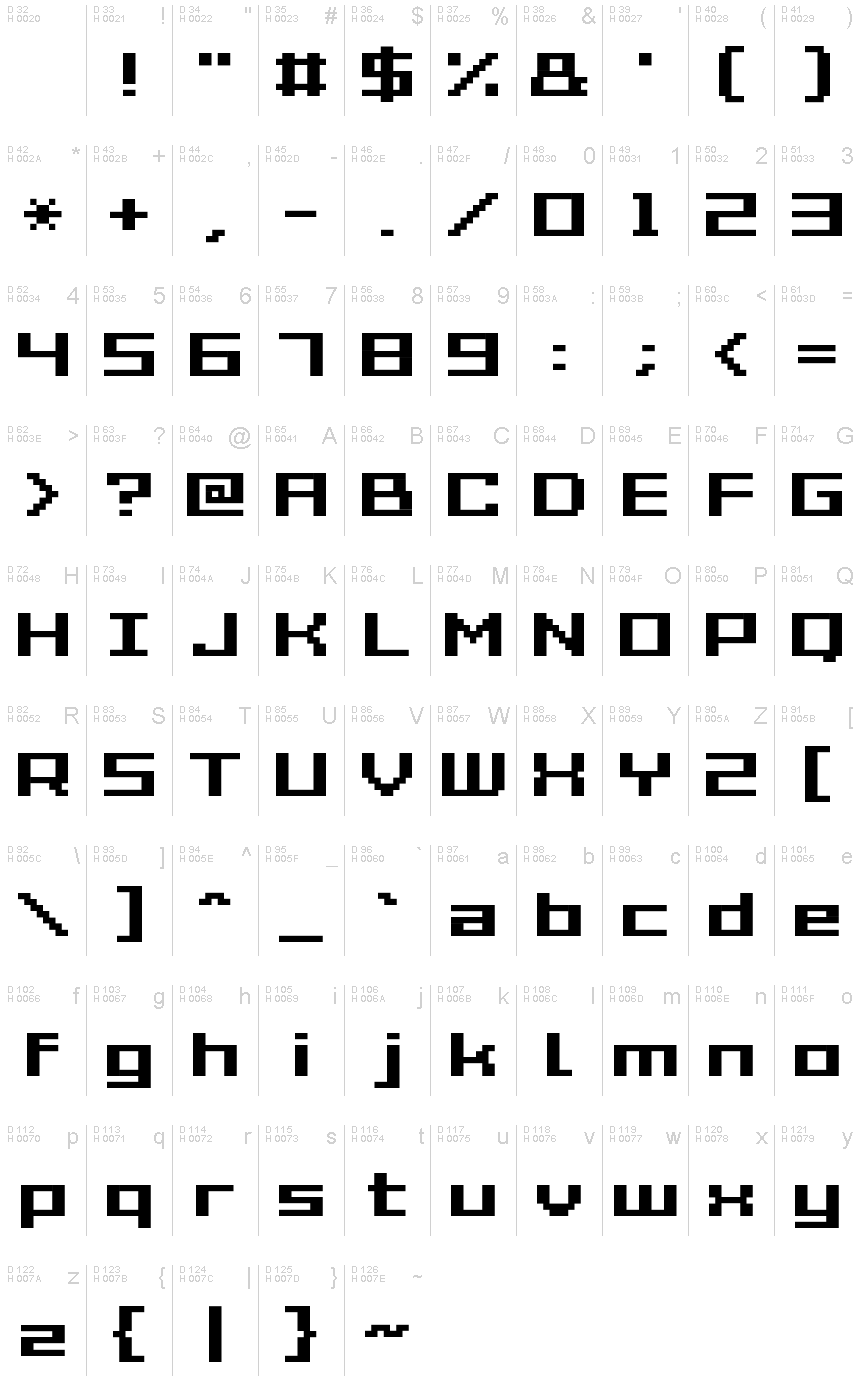
Grixel Acme 7 Wide Bold Xtnd
Grixel Acme 7 Wide Bold Xtnd to urzekający pikselowy krój pisma, który emanuje retro-futurystycznym urokiem. Jej szerokie, pogrubione kreski i charakterystyczne kwadratowe zakończenia nadają jej wyrazisty, przyciągający wzrok wygląd. Wyrazista, geometryczna estetyka jest dodatkowo wzmocniona przez bitmapową konstrukcję, która nadaje fontowi zachwycającą pikselową fakturę.
Ten wszechstronny krój doskonale sprawdza się w różnorodnych projektach, od inspirowanych stylem retro interfejsów gier po efektowne nagłówki i logotypy. Silne, geometryczne formy sprawiają, że jest to świetny wybór dla odważnych typograficznych kompozycji, a pikselowy charakter pozwala na bezproblemową integrację z pixel artem i cyfrowymi środowiskami o niskiej rozdzielczości.
Nikos Giannakopoulos